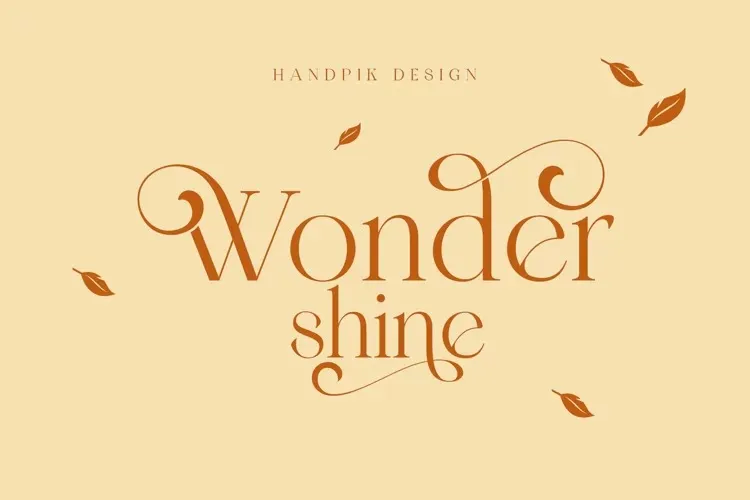
Wondershine Font – Download Grátis
A fonte Wondershine é uma escolha perfeita para designers que procuram uma serif moderna com forte presença visual. Originária do designer 99designs, esta fonte destaca-se por seu design assertivo e elegante, fornecendo um impressionante impacto em seus projetos. Ideal tanto para cartões de convite, decoração ou até mesmo produtos de moda, Wondershine é uma opção versátil que se destaca especialmente em aplicações que valorizam a leitura clara e a presença visual forte. Com um amplo conjunto de caracteres, incluindo letras maiúsculas e minúsculas, números, pontuação e suporte multilíngue, Wondershine expande suas possibilidades ainda mais. Além disso, oferece ligações gráficas e alterações estilísticas para adicionar um toque especial às suas criações, tornando-a uma escolha indispensável para designers que buscam dar seu trabalho um toque único e profissional. Seja você designer de moda, gráfico ou até mesmo criador de conteúdo digital, Wondershine é a fonte perfeita para seus projetos.